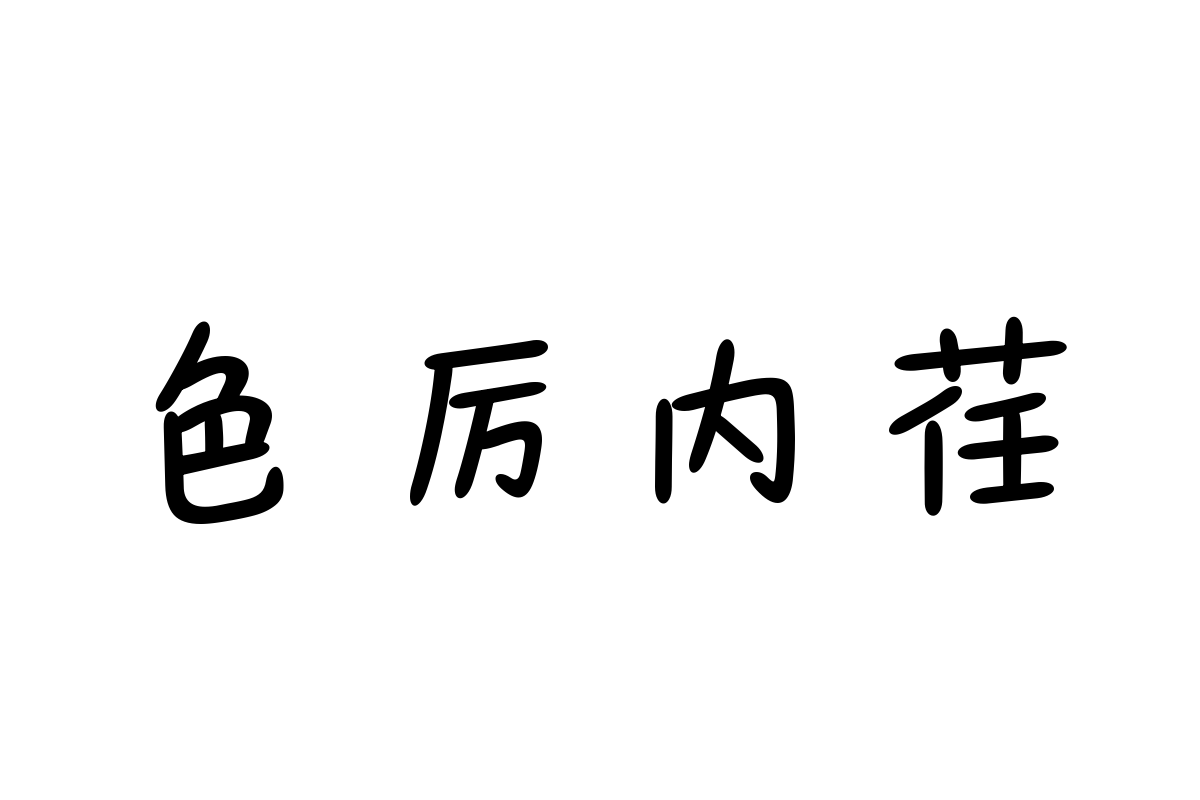
“三极六岁半”字体是一种专为儿童设计的字体,旨在吸引孩子们的注意力,让他们在阅读时感到愉快。这种字体通常具有鲜艳的颜色和简单的形状,以及大号的字号,以便于孩子们轻松阅读。此外,这种字体还可能包含一些有趣的图案或符号,以增加趣味性和互动性。总的来说,”三极六岁半”字体是为孩子们设计的,旨在帮助他们培养良好的阅读习惯。